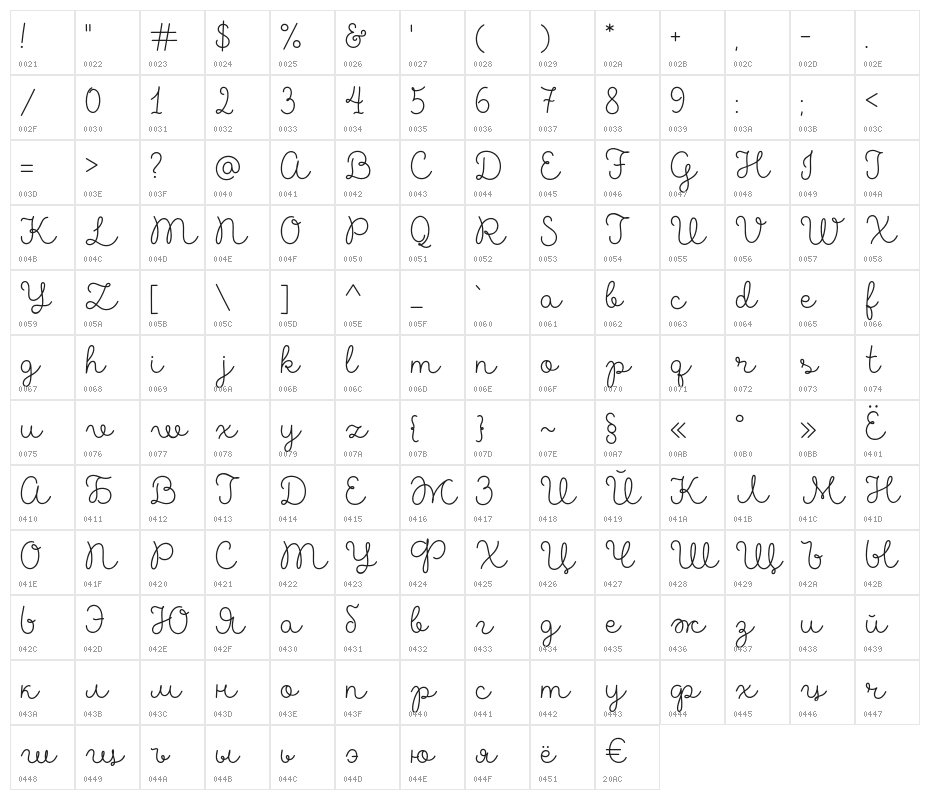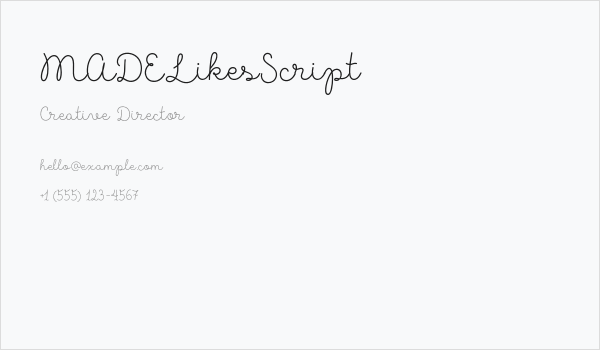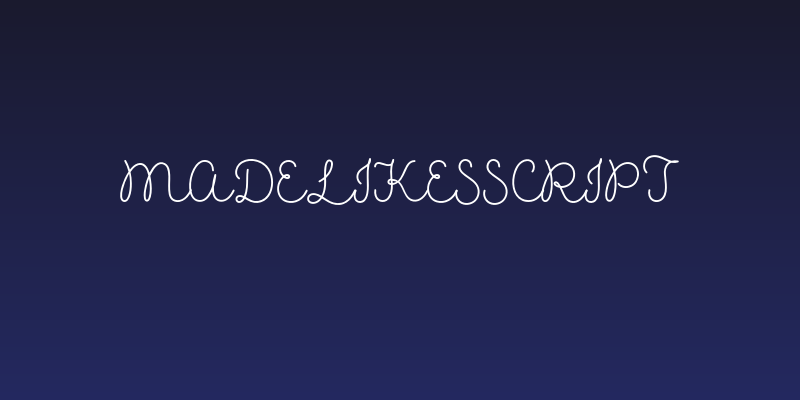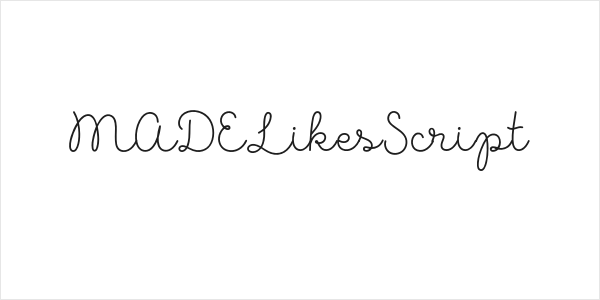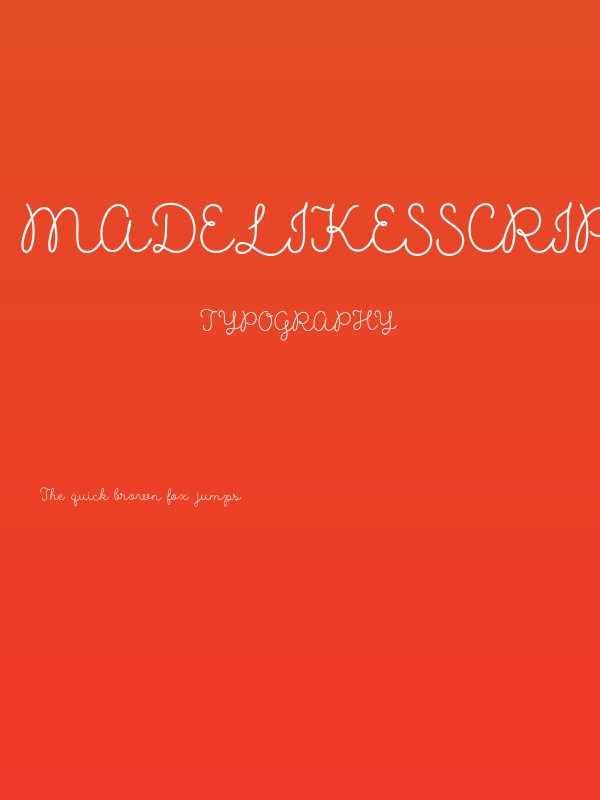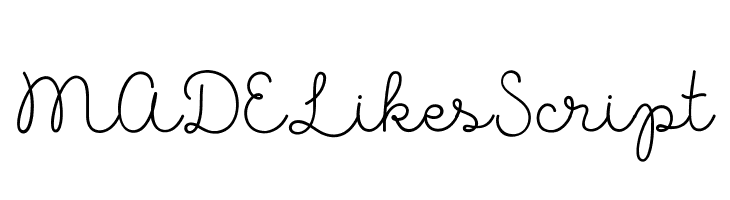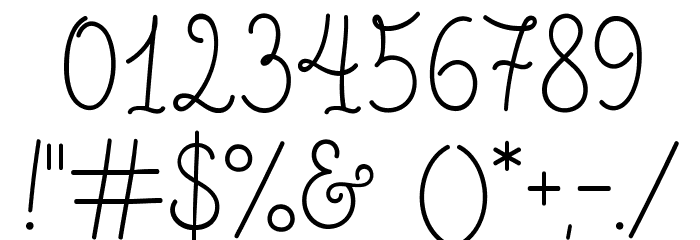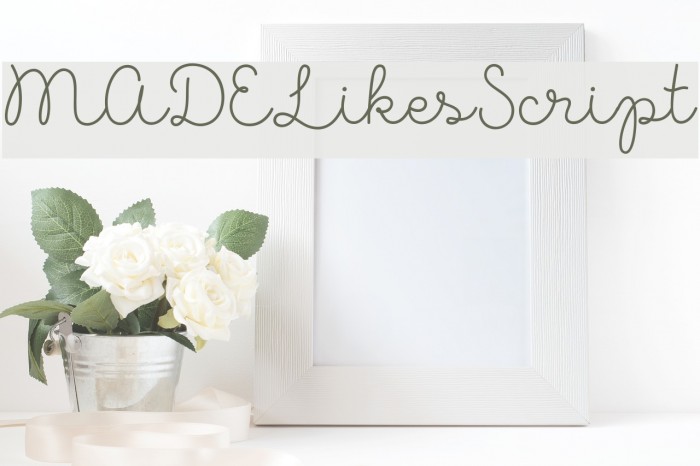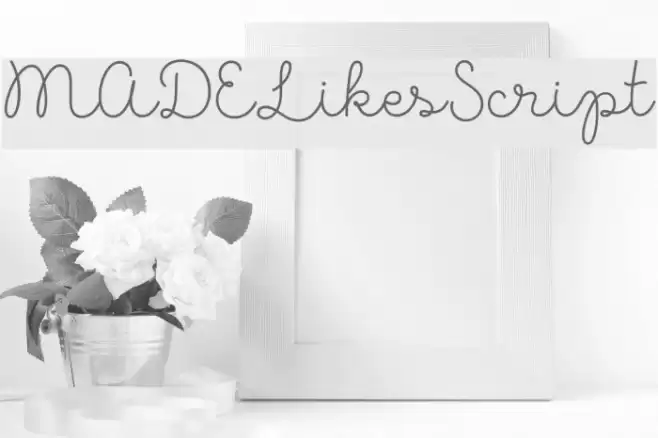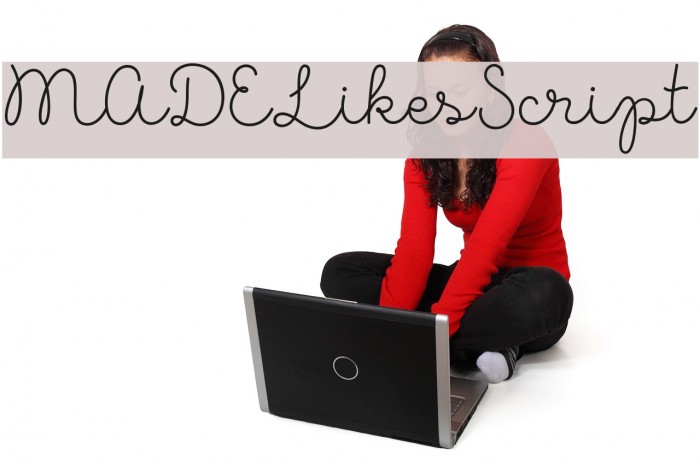
MADELikesScript Font
| Estilo geral | Whimsical, Playful |
| Caso de uso | Invitations, Greeting cards, Personal branding |
| Projetos propostos | Ideal for invitations, greeting cards, personal branding, and creative projects that require a touch of elegance and personality. |